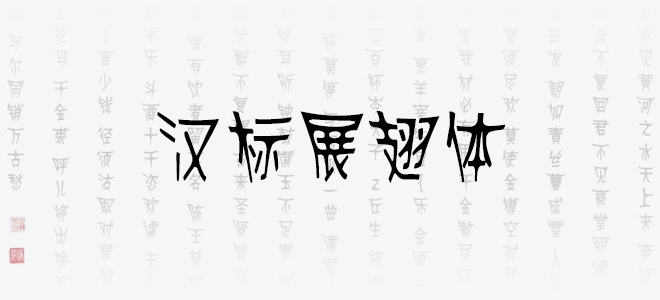
漢標(biāo)展翅體是漢標(biāo)字庫出品的一款藝術(shù)字體,根據(jù)黑體的字形創(chuàng)作而來,作者通過大量字體設(shè)計變形,使得字體有展翅感,從而展現(xiàn)美術(shù)視覺感,蘊含著深沉的藝術(shù)魅力,能給人以無限的美感,適用于包裝設(shè)計、電商、品牌名稱、漫畫、影視綜藝、游戲、各類商業(yè)海報、戶外廣告標(biāo)題等設(shè)計領(lǐng)域。
漢標(biāo)展翅體